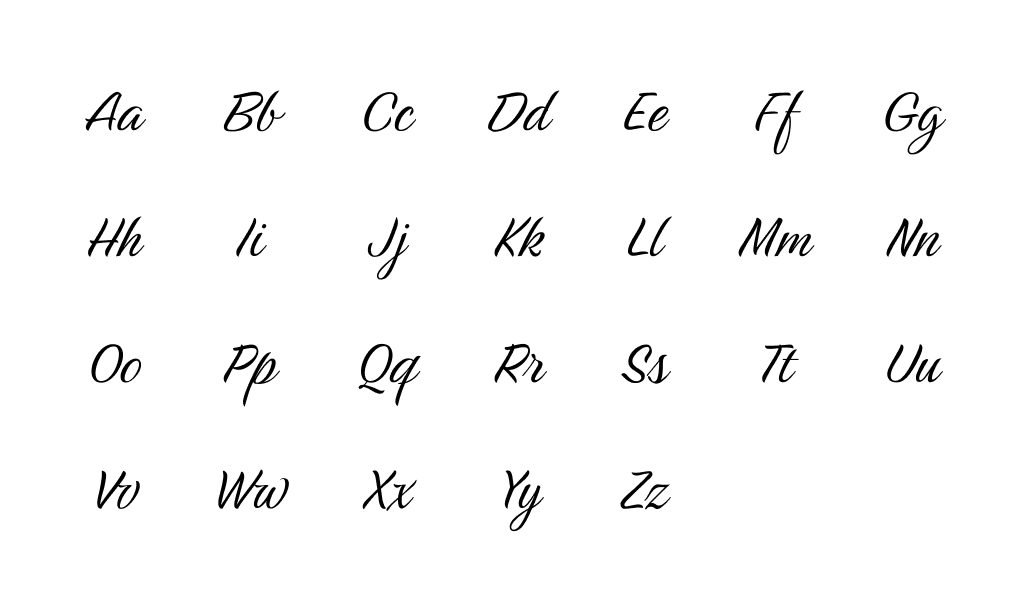
A tipografia existe na humanidade há centenas de anos. Cada um de nós entra em contato com esse fenômeno diariamente, folheando o feed de nossa rede social favorita, lendo composições nos rótulos dos produtos nas lojas e olhando outdoors.
A tipografia é o design visual do texto, um elemento importante da marca e um componente-chave da composição.
Criar logo onlineSabe-se que as pessoas dominavam a arte da inscrição há mais de mil anos, muito antes do surgimento de dispositivos especiais para impressão. Cada elemento foi cuidadosamente pensado, desenhado em forma de rascunho e só depois transferido para o papel no texto principal.
A tipografia inclui muitos aspectos: desde a diagramação de jornais e revistas até o desenvolvimento de fontes para logotipos. Com o desenvolvimento do progresso tecnológico, começou a se espalhar por toda parte: agora seus métodos e técnicas não são utilizados apenas em editoras.
A tipografia moderna é “responsável” não só pela legibilidade do texto, mas também pelo seu design gráfico.
A inscrição deve evocar certas associações e emoções no leitor, motivar ações específicas.
Antes de mergulharmos no fascinante mundo da tipografia, vamos concordar com algumas terminologias. Os termos “fonte” e “tipo de letra” são frequentemente usados de forma intercambiável: isso não é inteiramente verdade. Um tipo de letra é um conjunto de fontes, enquanto uma fonte é um dos estilos contidos em um tipo de letra.
Todas as fontes existentes são divididas em quatro tipos principais: antiqua, grotesca, manuscrita e display.
Antiqua (também conhecida como “estilo humanista”) é uma fonte com serifas, pequenos elementos que vão além dos componentes principais do personagem. Este é um dos estilos mais antigos e populares e é inspirado na caligrafia tradicional.
Acredita-se que a antiguidade surgiu há mais de 600 anos. As fontes serifadas são uma opção estrita e “formal” para documentos formais. Eles são frequentemente encontrados em publicações e documentos impressos. Essas fontes possuem diversas formas de execução, podem ser negrito, itálico, etc. O estilo serifado mais famoso é o Times New Roman.
O grotesco ganhou popularidade há relativamente pouco tempo – em meados do século XX. Do referido estilo humanista, distingue-se pelo aspecto gótico. A fonte é considerada mais moderna e clara, adequada para textos eletrônicos – é de fácil leitura nas telas. Esta fonte é uma excelente escolha para títulos. Seu “representante” mais famoso é a fonte Arial.
A fonte manuscrita é única devido à sua arte e curvas graciosas. Assim como o grotesco, a fonte manuscrita surgiu em meados do século XX. A vantagem das fontes manuscritas é a elegância e a beleza, a desvantagem é que são difíceis de ler: nem todos conseguem analisá-las com rapidez e facilidade. A escolha de tais estilos deve ser feita da forma mais responsável possível: a fonte deve atrair, despertar interesse e não repelir com sua complexidade.
A fonte de exibição é a mais incomum e informal de todas. As fontes são muito originais, memoráveis e criam um estilo único. Essas opções serão uma ótima opção para manchetes e logotipos.
As fontes se destacam em um grupo separado – são usadas em livros e publicações online. Sua principal vantagem é que são compreensíveis mesmo em tamanhos pequenos.
Elementos básicos da tipografia.
Conhecer os componentes básicos o ajudará a navegar melhor pela variedade de estilos e selecionar rapidamente o que você precisa.
Conduzindo, liderando – todas essas são designações do mesmo conceito – a distância entre as linhas. O espaçamento entre linhas definido corretamente torna o texto mais legível. Se o espaçamento entre linhas for mínimo, o texto torna-se ilegível e extremamente difícil de ler. Muita distância também complica a percepção – você precisa seguir o “meio-termo” e escolher um valor médio (por exemplo, a opção “padrão”).
O espaçamento entre letras, ou final, é a distância entre caracteres adjacentes. Muito pouco espaço entre as letras cria um efeito de encolhimento; muito pouco espaço torna difícil separar uma palavra da outra. Os parâmetros podem ser definidos manualmente – os programas modernos oferecem essa oportunidade.
Kerning regula o espaçamento entre letras apenas nas palavras: os valores não se aplicam a todo o texto. Na maioria das vezes, essa ferramenta é usada ao desenhar logotipos – ela permite implementar ideias estilísticas incomuns.
Um grafema é a menor unidade de texto: um símbolo (letra, número, sinal de pontuação).
Um glifo é uma representação gráfica de um grafema em um estilo específico.
Tamanho: O tamanho do personagem verticalmente.
Separadamente, diremos algumas palavras sobre letras – inscrições com estilos únicos, semelhantes às caligráficas. As letras não são o principal tipo de formação de fontes, mas costumam ser usadas para criar belas inscrições em banners, etc.
A tipografia é incrivelmente extensa e emocionante! Mergulhe no mundo dos tipos de letra e fontes: aprenda novos estilos e não se esqueça de experimentar combinações, pois só assim é possível encontrar uma identidade corporativa!